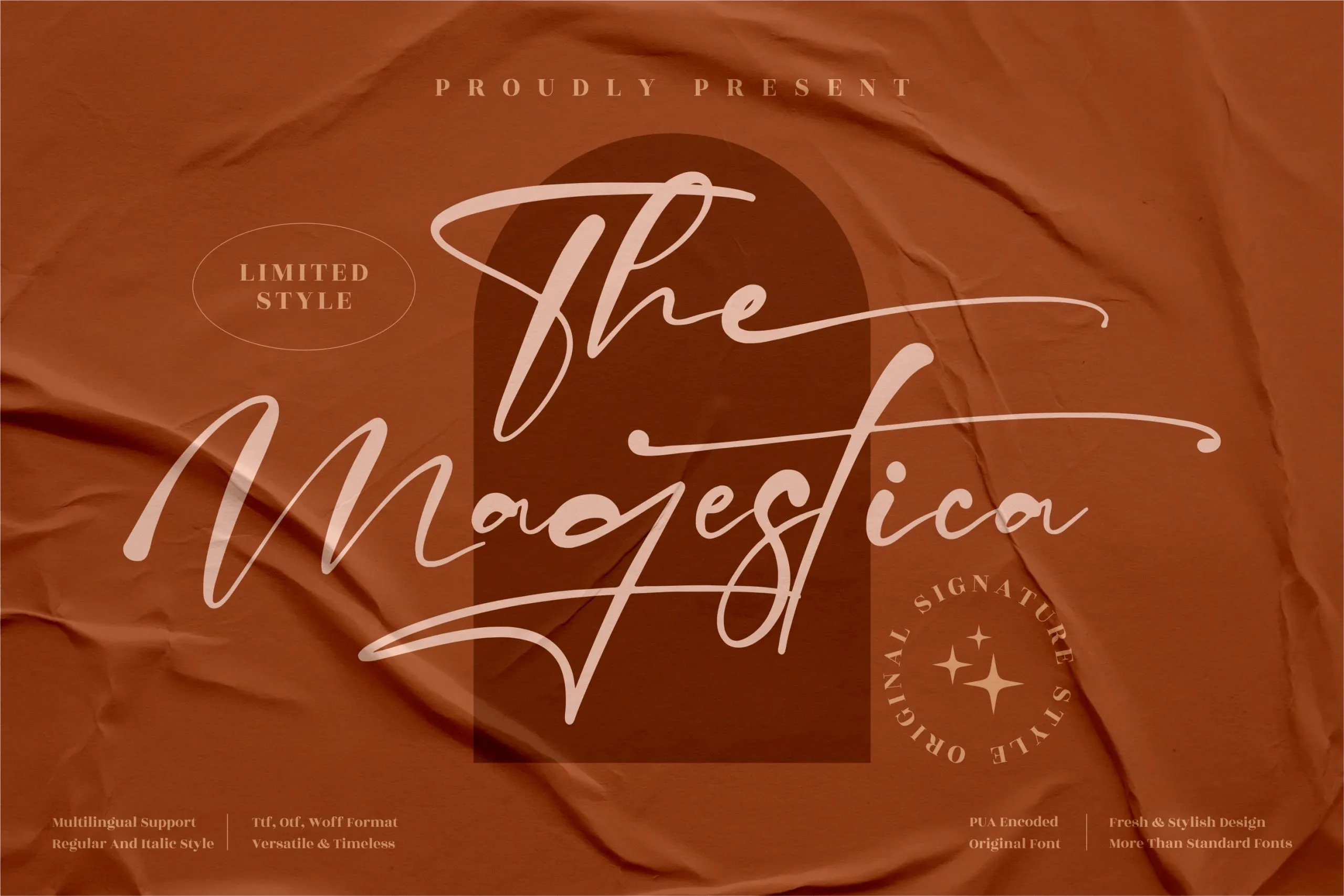
The Magestica Font – Download Grátis
A Magestica Font é uma escolha perfeita para quem procura criar design com um toque de luxo. Desenvolvida pelo estúdio Perspectype Studio, essa fonte é perfeitamente adaptada para qualquer projeto que você possa imaginar. Suas linhas elegantes e seu estilo autêntico garantem uma assinatura única e sofisticada para seu trabalho. Seja no design de logotipos, embalagens ou até mesmo nas etiquetas dos seus produtos, essa fonte oferece um toque diferenciado e respeitável que vai complementar qualquer projeto. Ela também é excelente para aplicativos em nível de escrita manuscrita, como postais, cartas de cumprimentos, camisetas personalizadas ou até mesmo para adicionar uma assinatura profissional ao seu trabalho. A Magestica Font não apenas adiciona um toque de sofisticação e elegância a qualquer projeto, mas também é versátil o suficiente para ser usada em múltiplas aplicações. Seja para ilustrar sua marca ou decorar um poster, essa fonte vai ajudá-lo a alcançar o nível desejado com uma assinatura única e profissional.